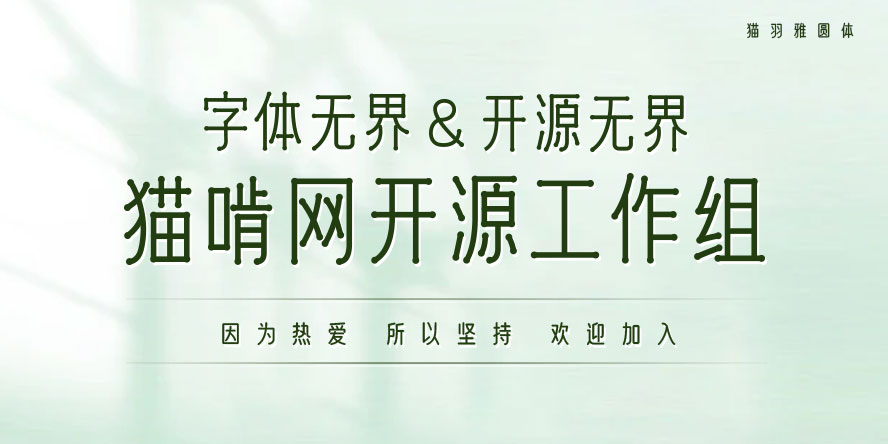
前段时间猫啃网发布投票结果,票数最高的是“佑字”这款字体。由于该字体的字数少且笔画复杂,不易于快速补充相应笔画和制作简体版,我们将尝试通过AI造字的方法来制作相应的笔画,待基本结构完成后再手工修补字体存在的问题,由于练字成功率较低,所以短时间不会发布该字体简体版。
以下是AI造字的测试样图:
票数第二高的是“叛逆明朝”字体,我们也已经与原作者取得联系,作者目前正在补充JIS一级字表。我们计划等作者补完相应的字表之后再开始补充相应的简体字部分。
关于无界黑
关于无界黑的字体的进展,给各位汇报一下,目前已经补完GB2312-80标准字数,现在在进行优化字形和筛选错误工作中,相信不久会发布该字体。
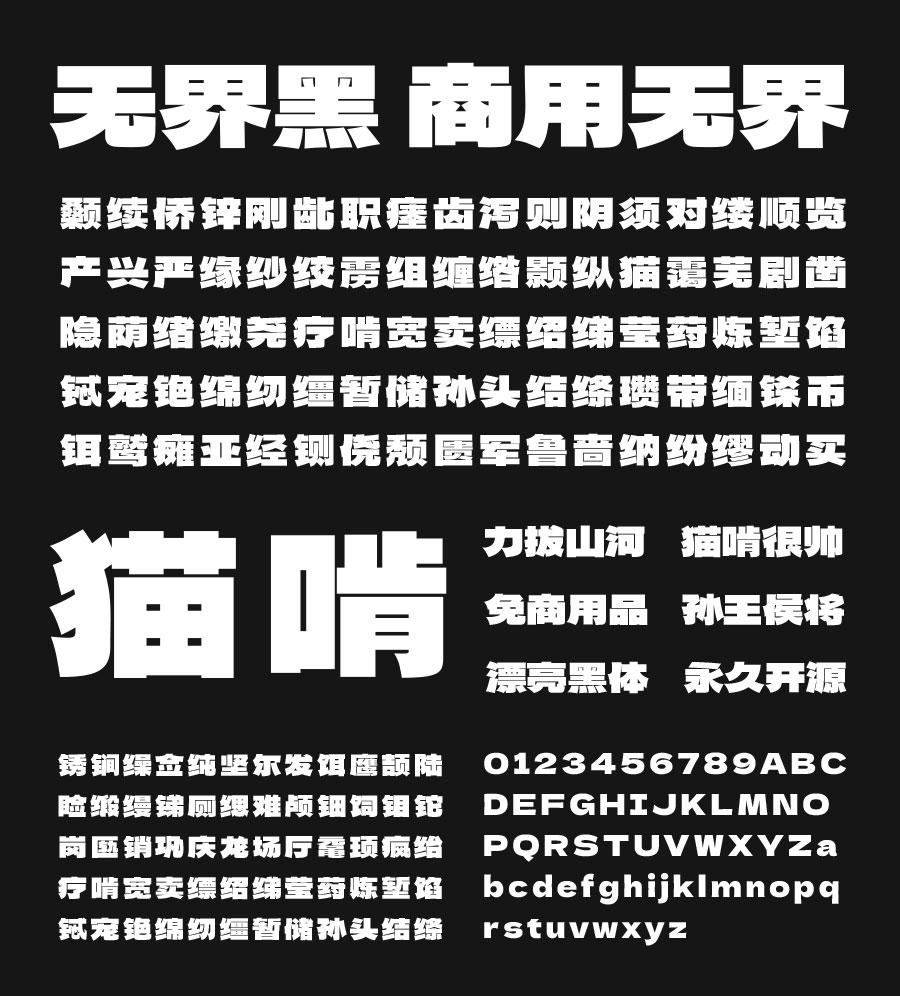
以下字表仅供展示,以实际发布字数为主:
关于什锦黑
什锦黑是@ZERO子主导对Nishiki-teki进行简体字补充的一款字体,目前也基本完成GB2312-80标准字数,正在进行字形优化及修正的工作,迟些也会发布。
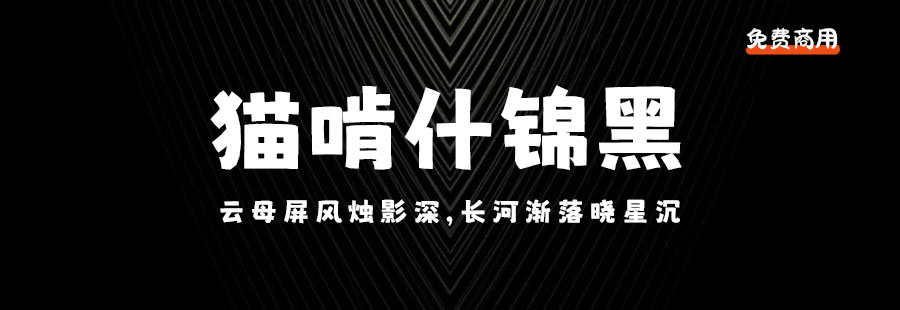
关于猫羽雅圆体
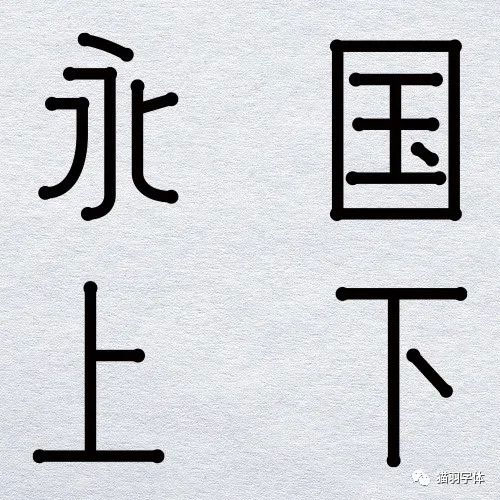
@猫羽兄也正在原创制作猫羽雅圆体(暂名),预计年内也会发布。猫羽雅圆体是猫羽原创的一款纤细优雅的无衬线体,笔画末端的圆形点缀让它更富细节。同样,这也造就了它美观典雅的字形特点,让它更加适用于如化妆品、美容店等女性用品的设计。
关于糖圆体
也来回应糖圆体的一些问题
接下来的半年,会把糖圆体的这个坑填上,优化糖圆体字形,预计年底发布糖圆体完整版。糖圆体多字重版本目前暂不考虑。
站长那个无界黑能字粗缩小一点点不
原版德拉黑体就是这么粗的~
可以到时能多做几个字号不呢站长
暂时不考虑做不同字重哦